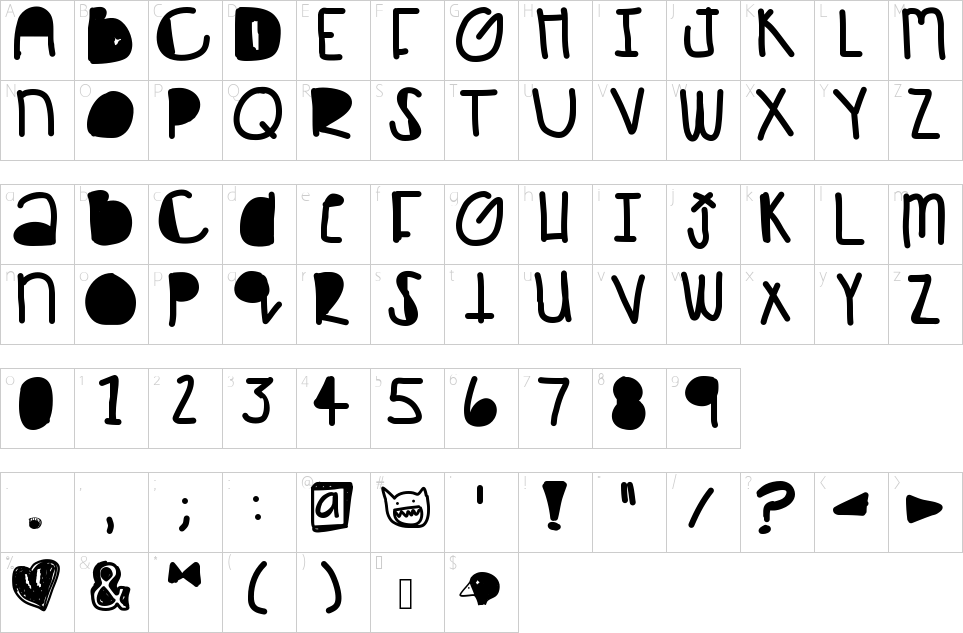
After Party Font
A fonte ‘After Party’ é uma seleção ideal para criar ambientes festivos e descontraídos, seja para uma festa de despedida ou para descontrair em um ambiente profissional. Desenvolvida por Des Gomez, esta fonte está disponível gratuitamente tanto para Windows quanto para Mac. Com sua design sensível à atmosfera descontraída e vibrante, ‘After Party’ se torna uma escolha ideal para se destacar em eventos sociais. Sucesso de download, ‘After Party’ já foi usada 4.519 vezes, refletindo sua popularidade e capacidade de ajudar a criar um entusiasmo único e atraente. Com uma coruja de desenho minimalista no topo, a fonte complementa perfeitamente os textos de festa, conferindo a eles um toque jovial e atual.
Mapa de caracteres da fonte After Party Font